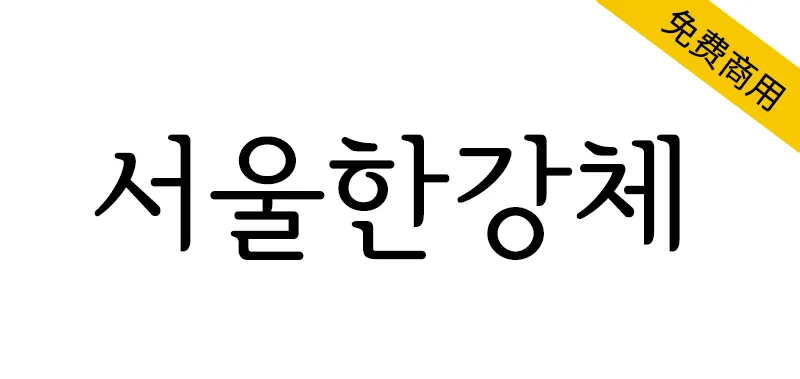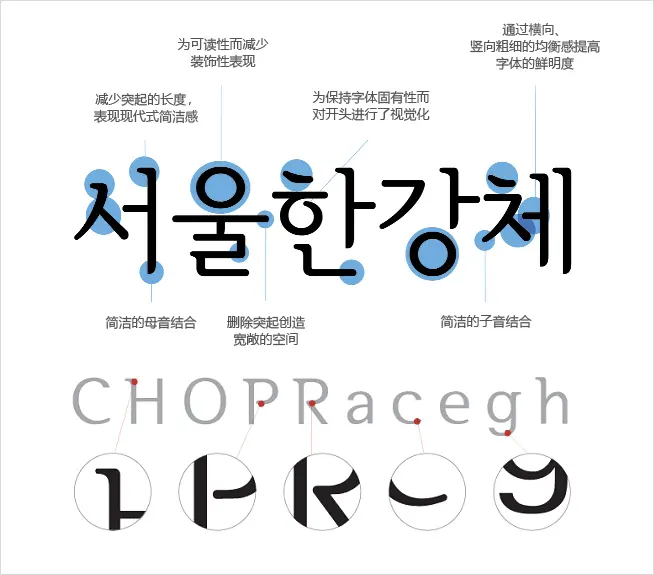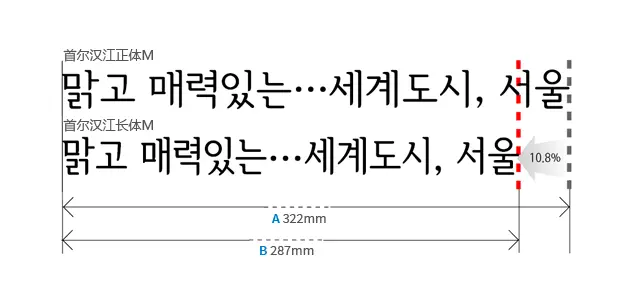
為普及首爾的固有字體,提升城市認同性與品牌價值,韓國首爾市開發出了明體系列的4種首爾漢江體(Light、Medium、Bold、Extra Bold)。
首爾字體中蘊含著剛正的儒士精神和淡雅的留白之美,從造型上展現了韓屋的開放和瓦片的曲線美。此外,首爾字體取名時採用首爾兩大代表性資源之一的“漢江”,更能激發市民對韓民族固有美麗語言——韓文的文化自豪感。
首爾市將首爾字體作為首爾的固有字體而推廣使用,首爾字體可提高城市認同性和品牌價值,開發了
首爾漢江體4種(Light、Medium、Bold、Extra Bold)
首爾漢江長體5種(Light、Medium、Bold、Extra Bold、black)。
首爾字體蘊含著正直的儒生精神和端莊典雅的含義,在造形上體現出韓屋的開放性和屋瓦的曲線美。
此外,字體名稱運用了首爾代表性資源之一的“漢江”,首爾字體將提高韓民族固美麗語言——韓文的文化自豪感。
減少突起的長度,表現現代式簡潔感
為提高可讀性而減少裝飾性筆畫
為保持字體固有性而對開頭進行了視覺化
通過橫向、豎向粗細的均衡感提高字體的鮮明度
簡潔的母音結合
刪除突起部分,創造寬敞空間
簡潔的子音結合